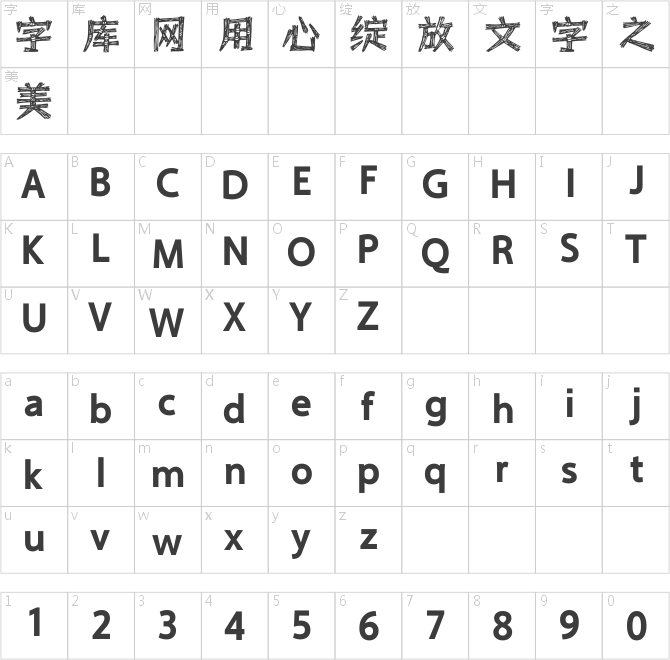
方正字迹-兰梓蓑笠翁体
“孤舟蓑笠翁,独钓寒江雪”。本款字体用粗犷、原生态的笔画线条,去模拟垂钓老翁身披蓑衣之状。每个字都具有拟人化的效果,而且字体的结构吸纳了POP字体的一些特点,在字形上显得不呆板,生动有趣、灵动活泼,具有“象形”意味。字中有画,字画结合,特别适合用于创意类以及儿童相关的广告设计、产品包装等。
作者张惟梓,擅长绘画、摄影及美术字设计等,长期从事企业文化、宣传及产品设计开发工作,摄影及美术作品曾多次参加省市级展览。